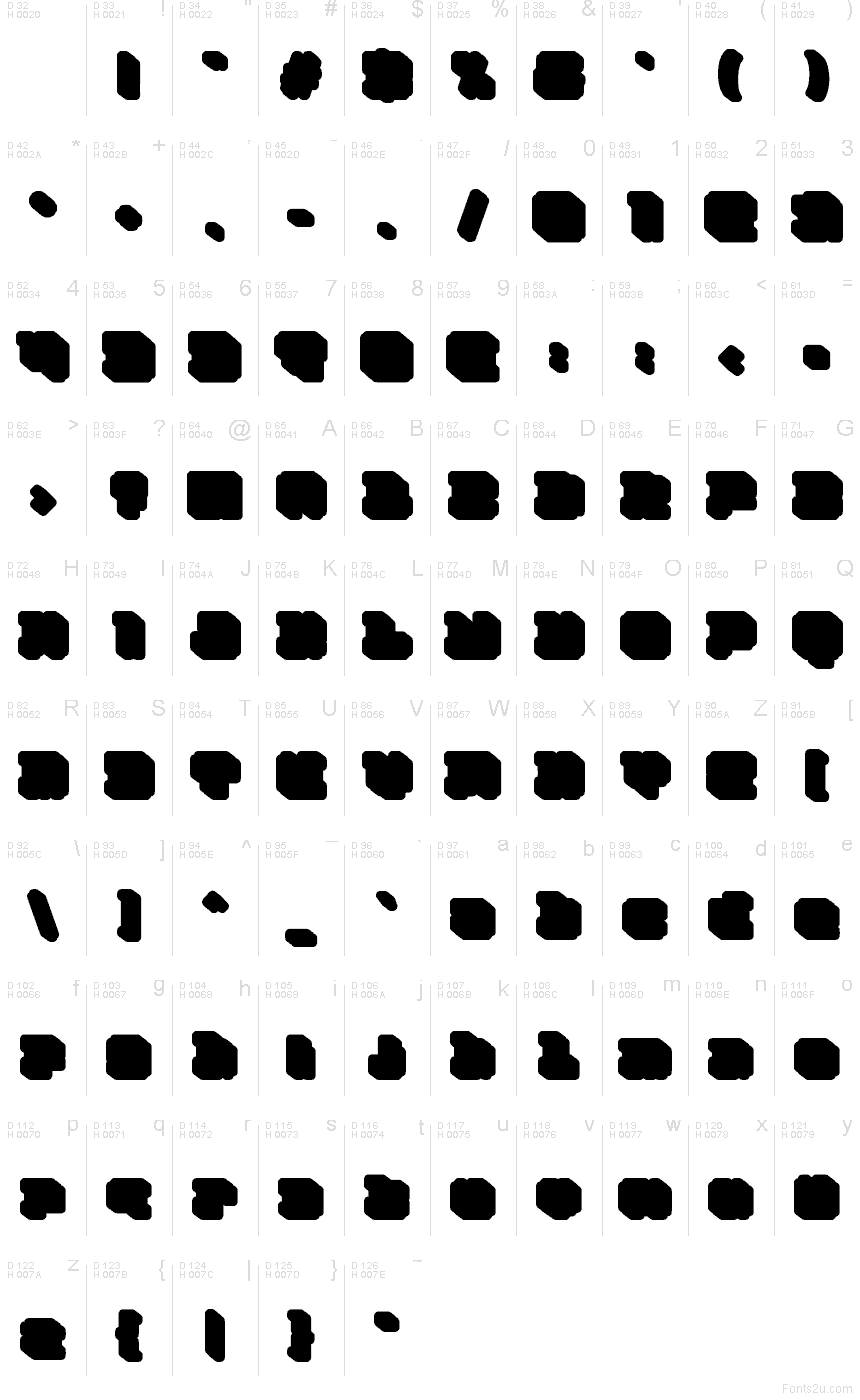
Techno Wave Two od Putracetol Studio je bezplatné techno písmo typu display, jehož silueta připomíná řadu zaoblených černých modulů s hlubokými diagonálními odsazeními, která vytvářejí solidní 3D efekt. Toto opakující se rozšíření připomínající stín dodává písmenům hustý, nízko-profilový rytmus, takže design působí spíše jako odlévané značení než jako neutrální futuristické písmo.
Hodí se pro názvy her, hudební letáky, plakáty na technologické akce, streamovací grafiku a reklamní záhlaví aplikací, kde krátká slova potřebují kompaktní, syntetický blok barvy. Široké zaoblené rohy a výrazná hloubka se také hodí pro návrhy log a etikety na obaly, zejména pokud chcete dosáhnout hloubky bez použití obrysů nebo přechodů.